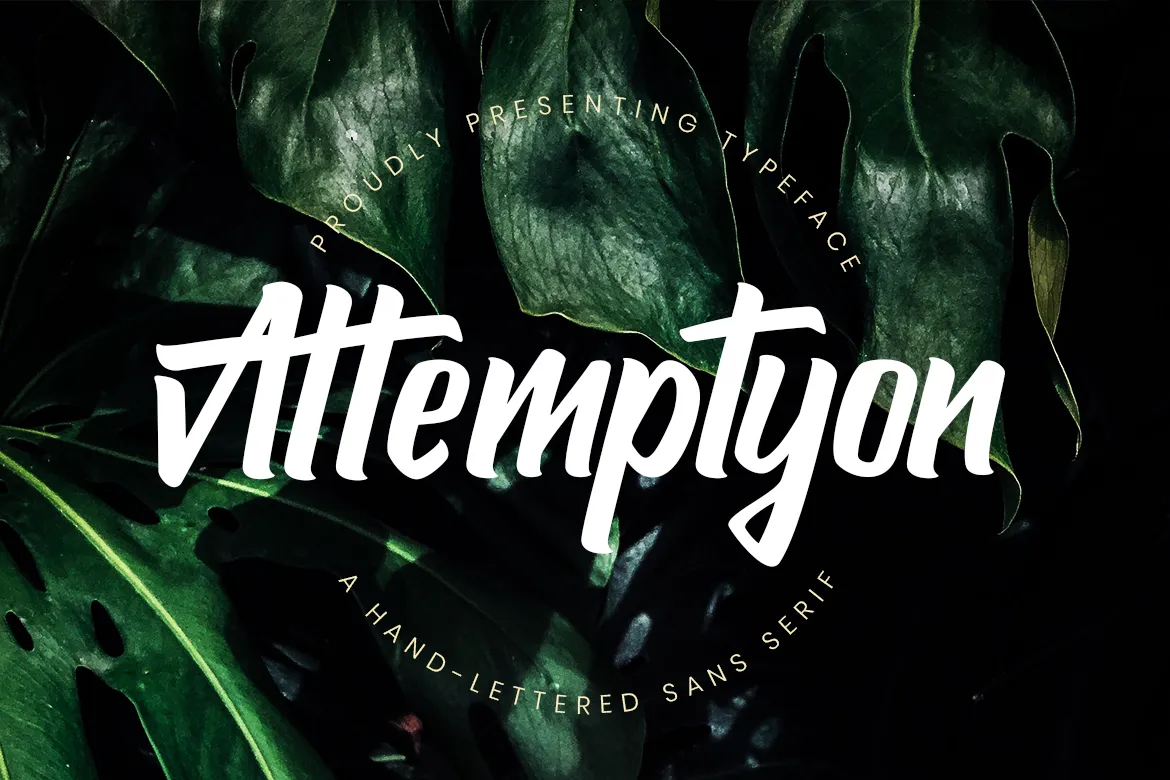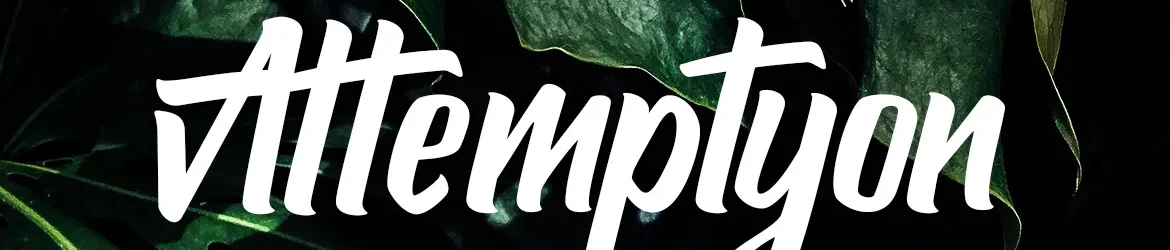
Attemptyon Handwritten Font – Download Grátis
Olha para essa nova adição do mundo dos Fonts no seu ateliê digital! A Attemptyon Handwritten Font é uma proposta inovadora na categoria de Script Fonts, criada pelo designer zziplex. Introduzimos uma tipografia bold e escrita à mão que traz o charme da graça, mas em um formato sans-serif moderno e elegante. Seja para projetos de marca, logos, criações para casamentos, postagens nas redes sociais, anúncios, embalagens, produtos, etiquetas, fotografia ou até mesmo o toque personalizado dos impressos, a Attemptyon é perfeita. Adquira agora e traga um pouco de escrita à mão para seus projetos digitais!